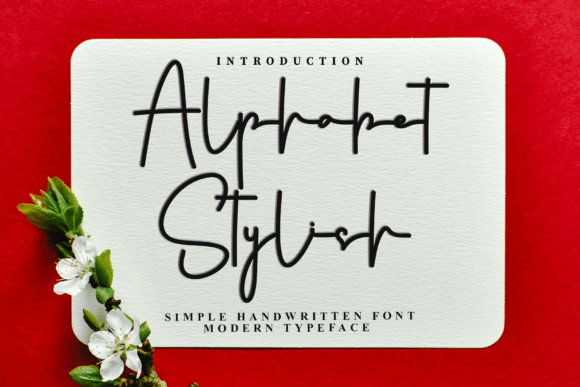
Alphabet Stylish Font
Alphabet Stylish Fontのような高品質の素材をお探しの場合、このプレミアムパッケージはクリエイティブなプロジェクトに素晴らしい選択です。
POD(オンデマンド印刷)製品、結婚式の招待状、またはソーシャルメディアのグラフィックを作成している場合でも、Alphabet Stylish Fontは理想的です。